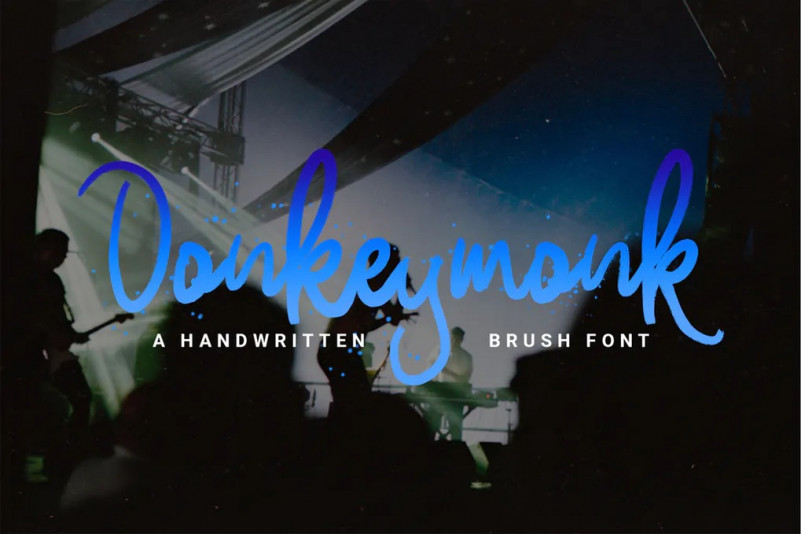
Donkeymonk Font
Donkeymonk est une police brossée à la main, avec des imperfections authentiques de pinceau sec, et une base très rebondissante Il a une police de pinceau parfaitement jumelée. Idéal pour les Logos, citations manuscrites, emballage de produits, en-tête, affiche, marchandise, médias sociaux et cartes de vœux.